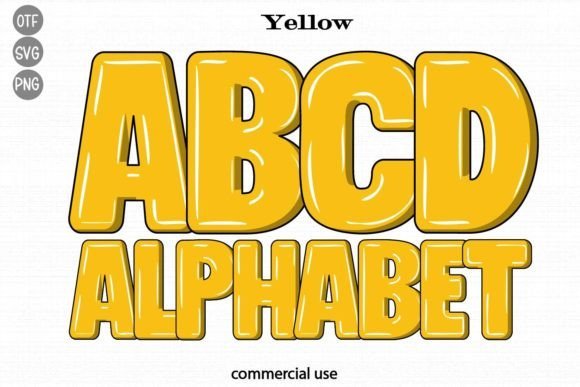
Yellow Font
Yellow Font – خط احترافي لإبداعك البصري
أضف لمسة من التميز والتألق إلى تصاميمك مع Yellow Font، الخط العصري الذي يجمع بين الأناقة والوضوح ليمنح أعمالك مظهرًا احترافيًا وجذابًا. مثالي للمصممين وصانعي المحتوى الذين يبحثون عن خط مميز لاستخدامه في الشعارات، الإعلانات، السوشيال ميديا، والعلامات التجارية.
???? المميزات:
✅ تصميم أنيق وسلس يناسب مختلف الاستخدامات
✅ يدعم الحروف الكبيرة والصغيرة لمرونة في الاستخدام
✅ مناسب للعناوين الجذابة والنصوص الإبداعية
ارتقِ بتصاميمك إلى مستوى جديد مع Yellow Font – الخيار المثالي لمحبي الإبداع! ????